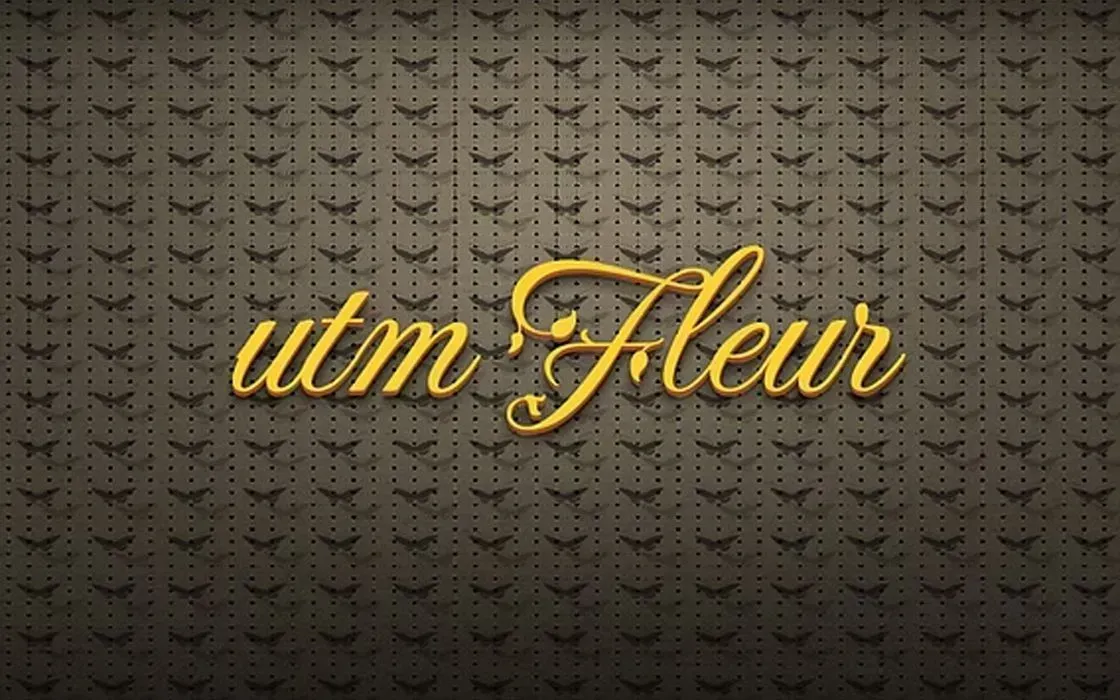
UTM Fleur là một font chữ script (viết tay) mang phong cách duyên dáng, mềm mại và đầy cảm xúc, được thiết kế như những nét bút lướt nhẹ trên giấy. Các đường cong uyển chuyển, kết nối mượt mà giữa các ký tự giúp font tạo nên cảm giác nữ tính, dịu dàng và sang trọng – rất thích hợp cho những thiết kế đề cao tính thẩm mỹ và tinh tế.
Từng chữ cái trong UTM Fleur như được chăm chút kỹ lưỡng với các đường nét thanh mảnh, dứt khoát nhưng không thô cứng. Font phù hợp để sử dụng trong các thiết kế như: thiệp cưới, logo thương hiệu mỹ phẩm, spa cao cấp, tiêu đề blog thời trang, bao bì sản phẩm handmade, hoặc ấn phẩm dành cho phụ nữ.
Font gốc Fleur Script là một thiết kế mang ảnh hưởng từ phong cách thư pháp hiện đại, thường được dùng trong branding và các sản phẩm mang yếu tố cảm xúc. Dù không phổ biến đại trà, nhưng đây là một font có tính thẩm mỹ cao và dễ ứng dụng.
Nếu bạn đang tìm kiếm một font chữ viết tay mềm mại, trang nhã và giàu cảm xúc, thì UTM Fleur chắc chắn là lựa chọn lý tưởng để mang lại vẻ đẹp nhẹ nhàng nhưng vẫn đủ sức thu hút cho dự án của bạn.